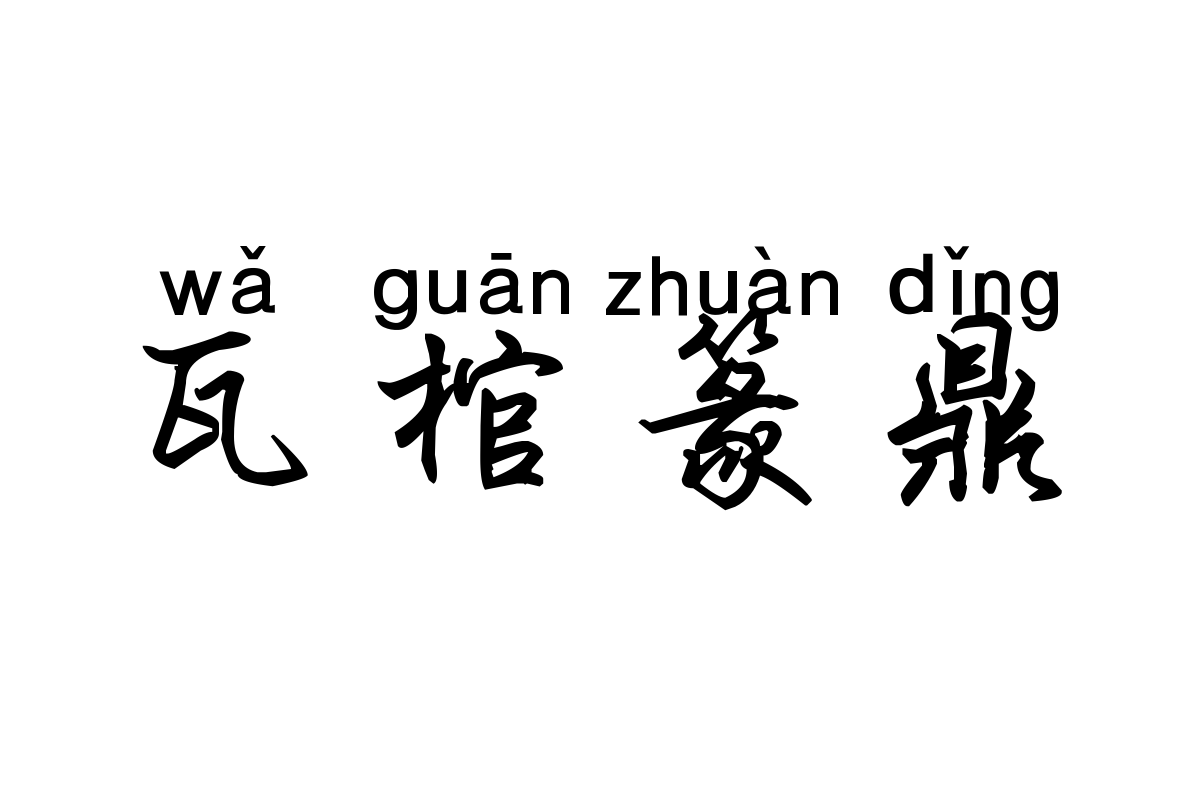
米开细行楷拼音体是一种中文字体,由著名书法家米开细先生设计。这种字体的特点是笔画清晰、结构紧凑,非常适合用于书写和排版。它的字形规整,线条流畅,给人一种优雅的感觉。
米开细行楷拼音体的特点如下:
1. 笔画清晰:这种字体的笔画非常清晰,无论是横、竖、撇、捺等基本笔画,还是复杂的连笔,都能准确无误地展现出来。这对于书法爱好者来说,无疑是一种福音。
2. 结构紧凑:米开细行楷拼音体的字形结构紧凑,使得整个字体看起来更加和谐统一。这种特点使得它在排版时能够更好地与其他字体融合,形成美观的视觉效果。
3. 线条流畅:米开细行楷拼音体的线条流畅,给人一种优雅的感觉。这使得它在书写时能够更好地传达出作者的情感和意境。
4. 适用范围广:由于米开细行楷拼音体的笔画清晰、结构紧凑、线条流畅等特点,它适用于各种场合,包括书籍、报纸、杂志、广告、网页等。这使得它成为了一种非常实用的字体。
总的来说,米开细行楷拼音体是一种非常优秀的字体,它以其清晰的笔画、紧凑的结构、流畅的线条和广泛的应用范围,赢得了广大用户的喜爱。